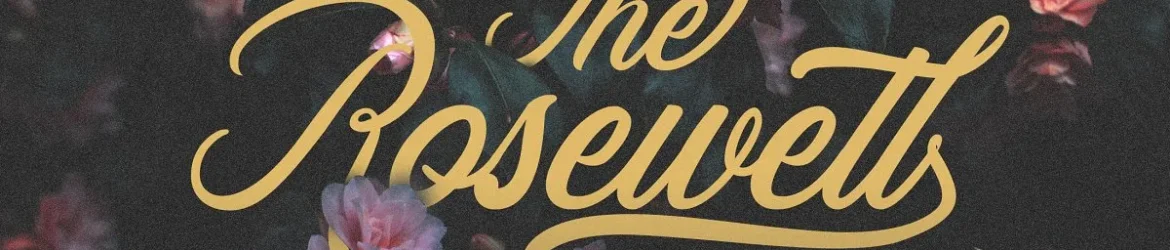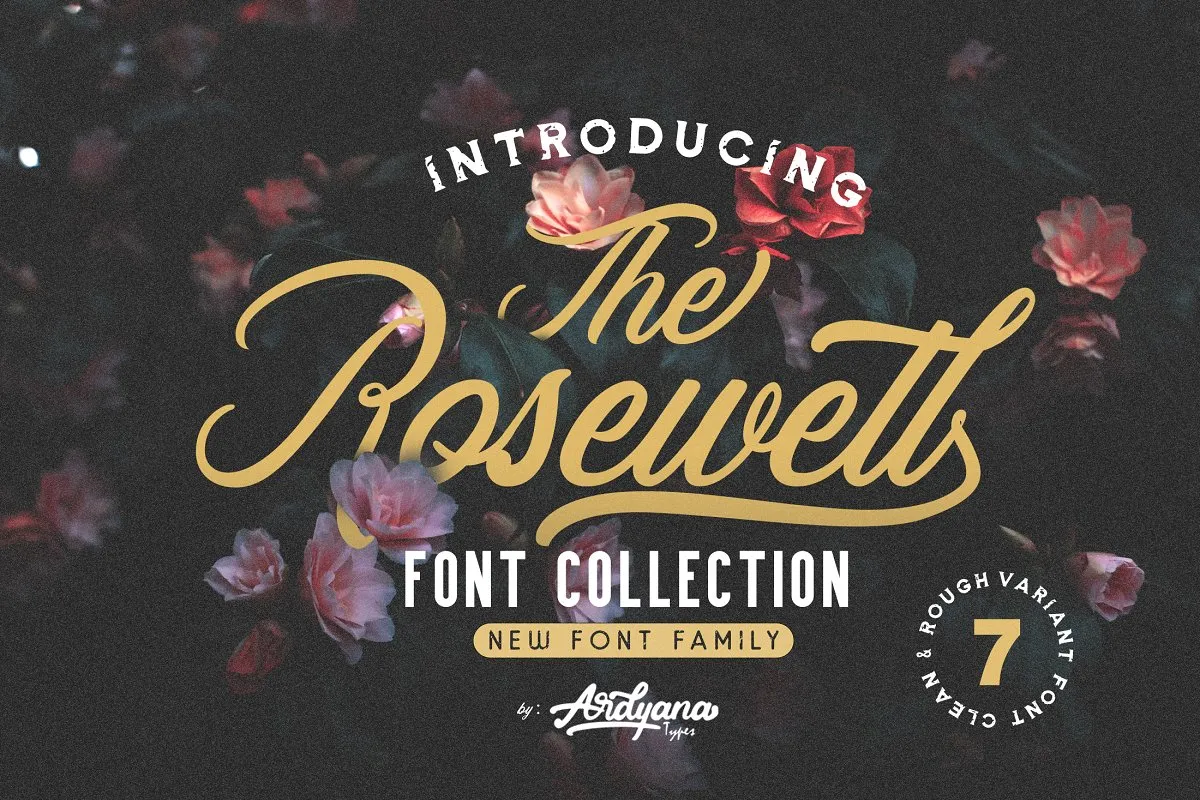
Rosewell Script Font
Olá amigos! Introduzimos a Rosewell Font! Ela foi projetada pela Ardyanatypes. A Rosewell Script Font apresenta 7 variações de fontes diferentes, com diferentes acentos. A Rosewell tem um tipo interessante de escrita e uma tipografia sans-serif que combina para torná-la ainda mais elegante e incrível. A Rosewell possui dois caracteres diferentes em cada letra sans-serif, incluindo limpos e rústicos para dar o impressiono retro. A própria Rosewell foi inspirada por várias artes de escrita a mão frequentemente ornadas em cafés e salas de estar, bem como pela arte mural urbana eccentricamente característica, o que faz da Rosewell ainda mais única quando usada. O autor manteria esta fonte parecendo elegante, sofisticada, fácil de ler, estilizada, fácil de lembrar e simplesmente fácil de usar. A Rosewell é a escolha perfeita para design de logotipos, frases, capas de álbuns, cartazes, cartões de visita e projetos gráficos muitos outros.